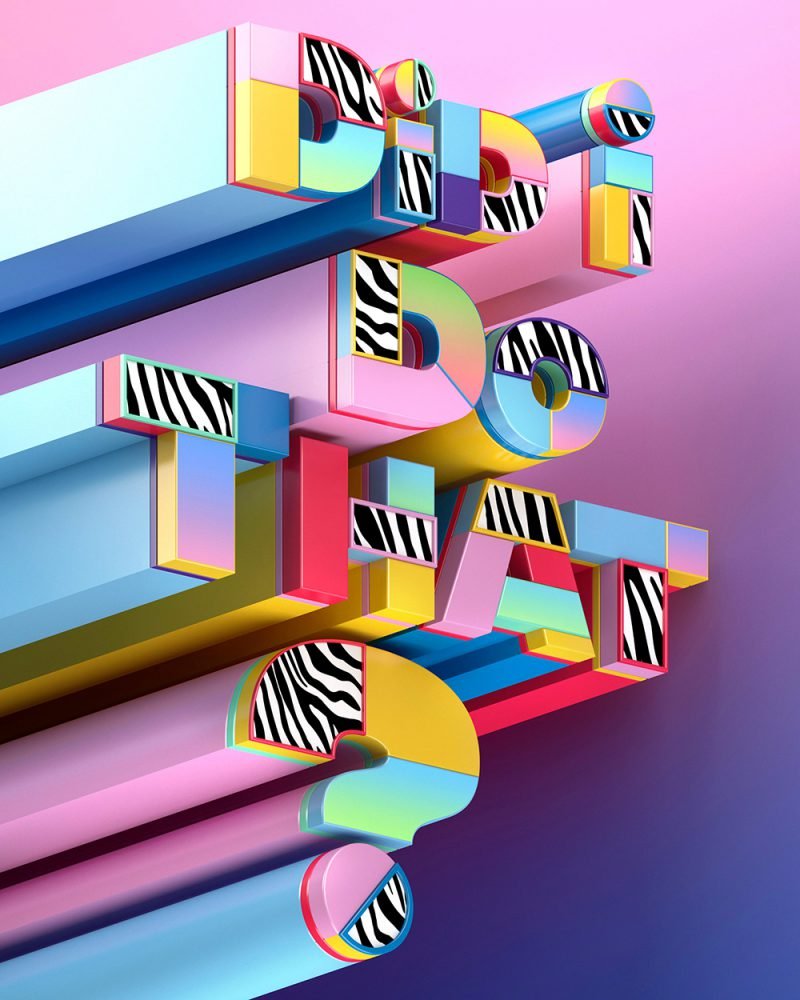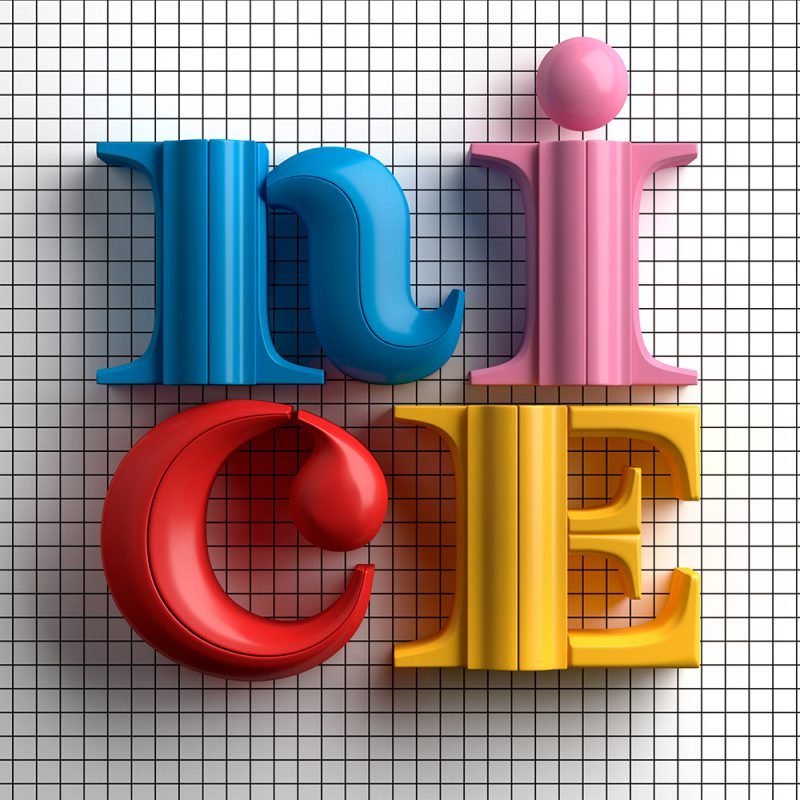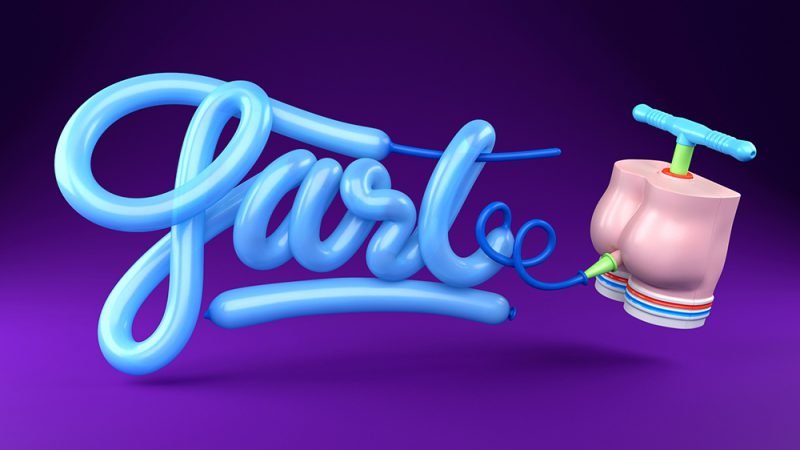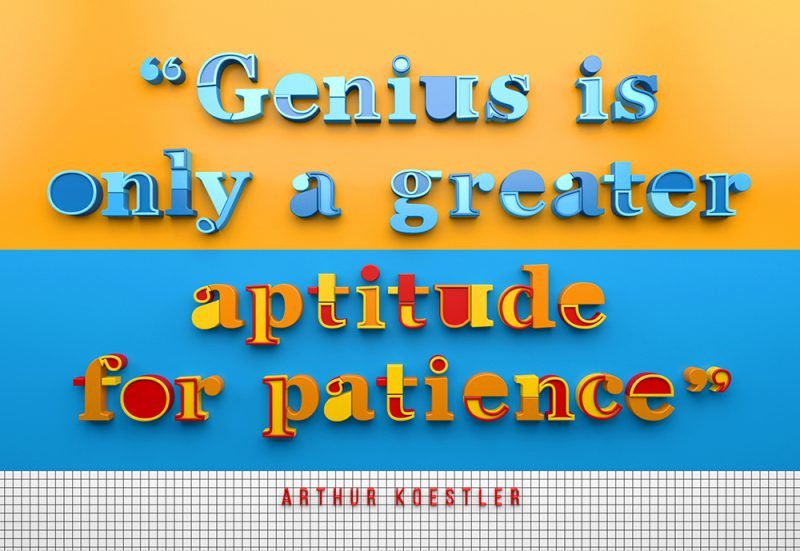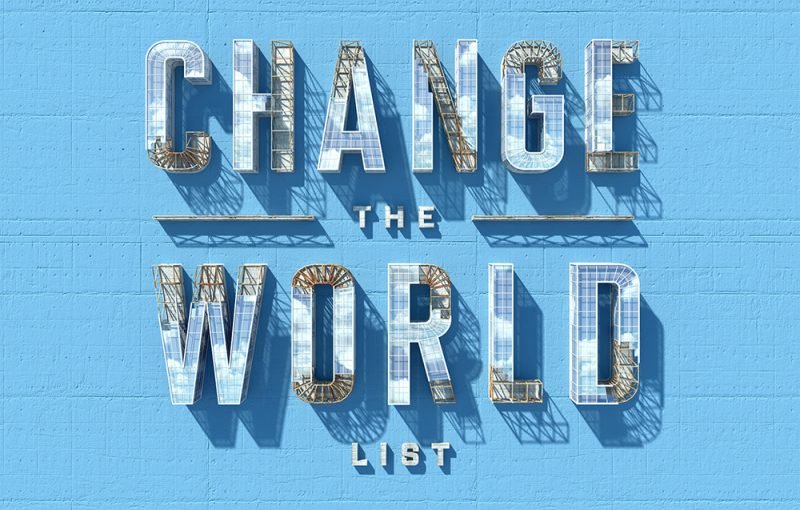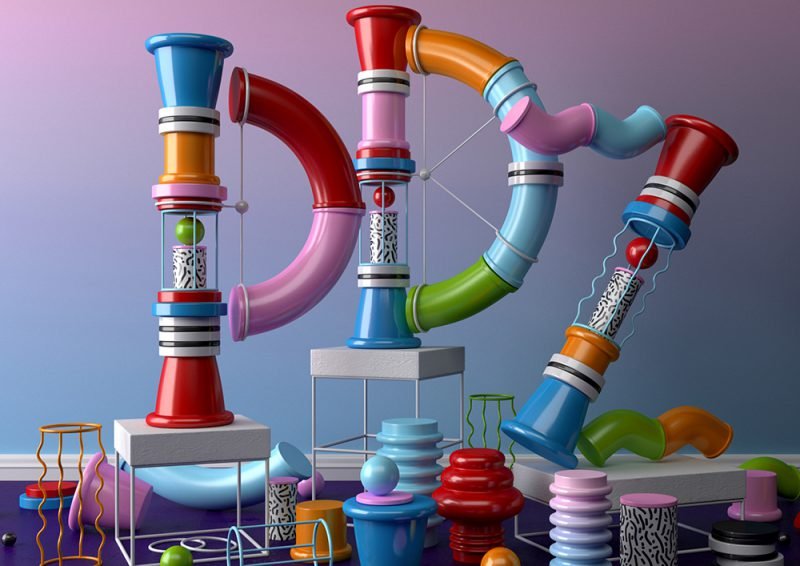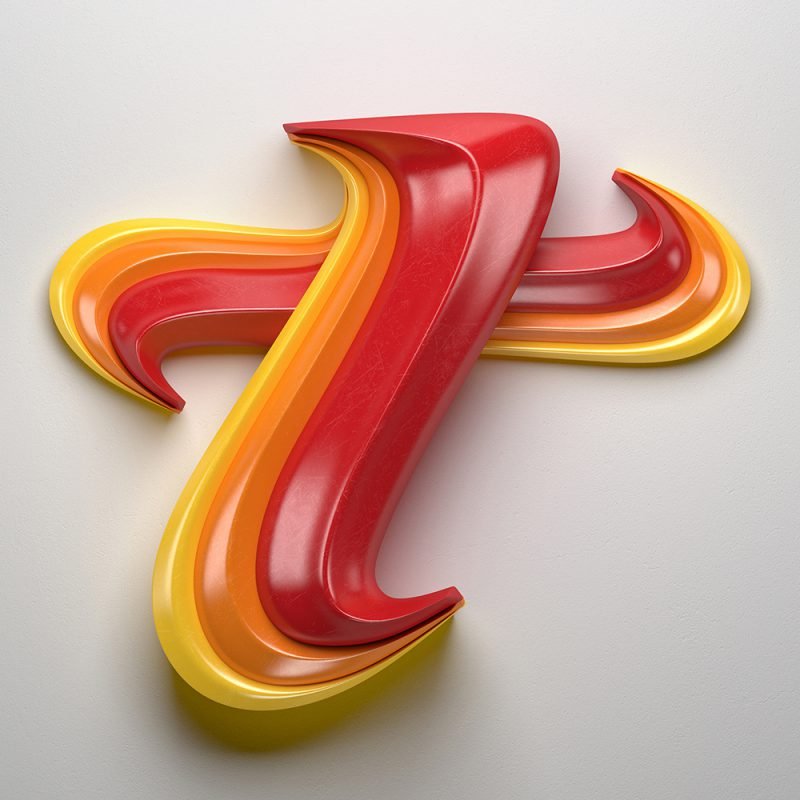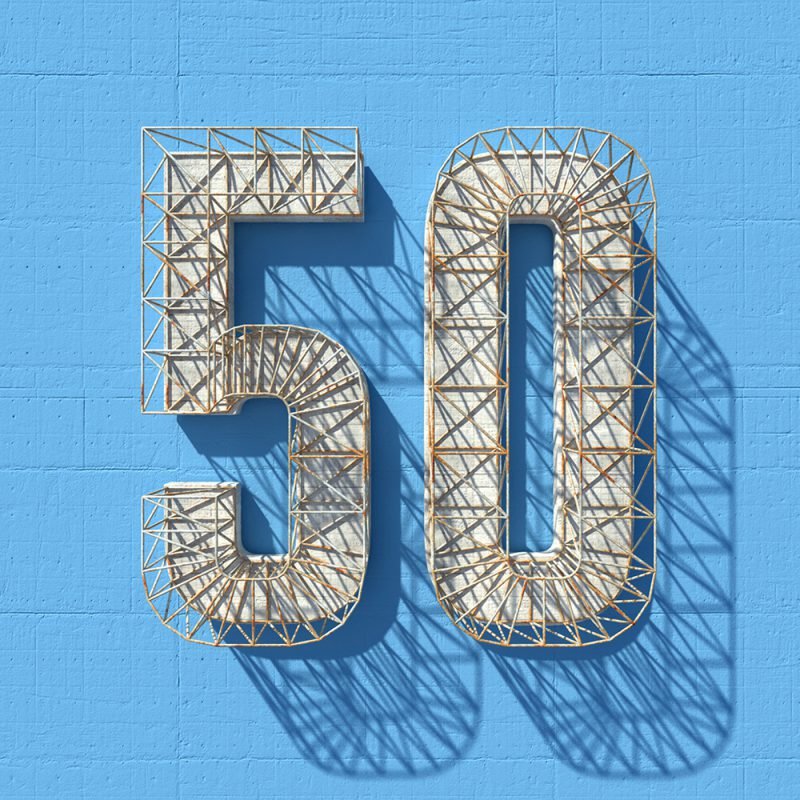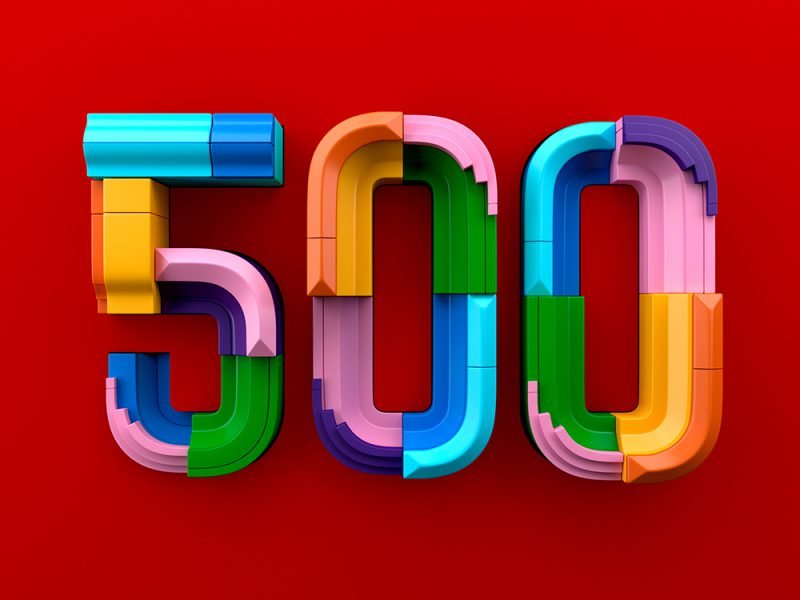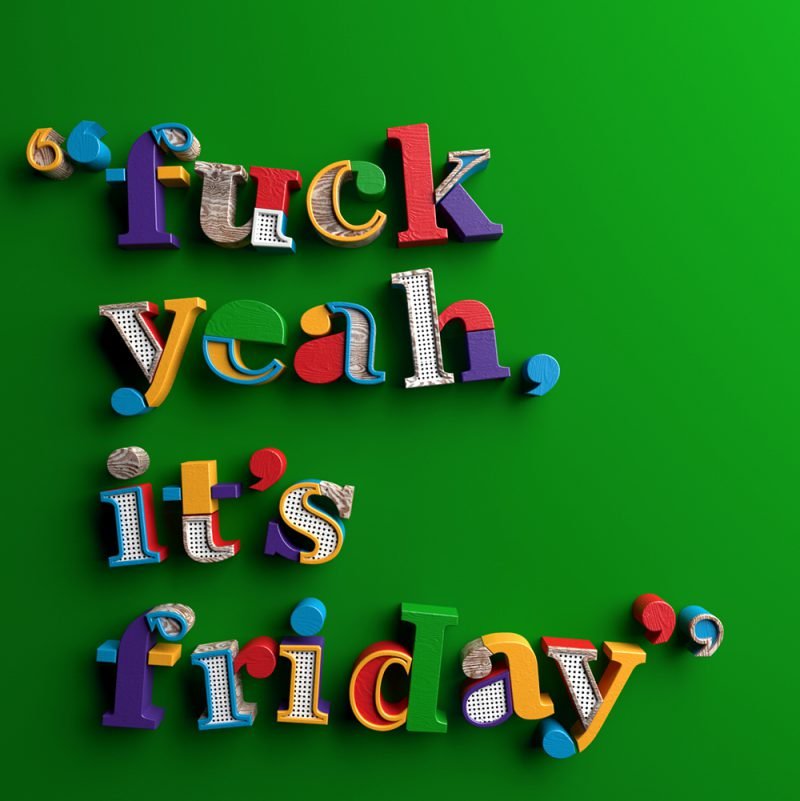
Ilustración digital 3D: las series tipográficas Muokkaa Studio
Composiciones volumétricas y coloridas
Alejandro López Becerro es el diseñador detrás de Muokkaa, el alias bajo el cual reúne una variada colección de series tipográficas. Especializado en ilustración 3D, el creativo nacido en Salamanca estudió diseño gráfico en la Escuela de Arte de la ciudad. Luego de trabajar dos años en un estudio local, y otros cinco como artista de motion graphics para televisión, comenzó a desempeñarse como creativo independiente. En sus composiciones, elabora coloridas tipografías en las que sobresalen llamativas tramas y volúmenes corpóreos. Entre sus trabajos, se destacan ilustraciones para publicaciones como Billboard, Fortune, Wired y marcas como Directv, Heineken y Refinery29.
Ilustración digital 3D: las series tipográficas Muokkaa